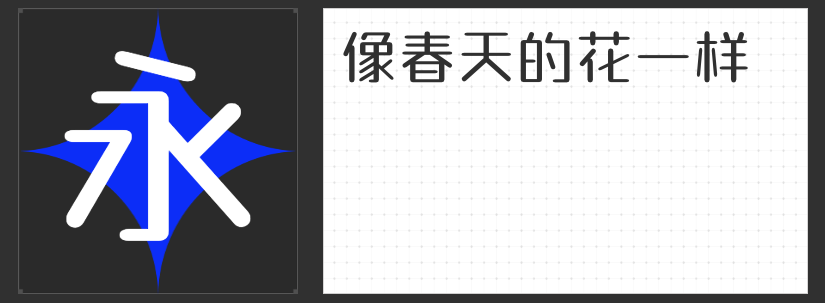
电商设计进阶指南:四款高辨识度字库字体解锁视觉吸引力
在电商视觉竞争白热化的当下,字体的选择直接影响用户的第一眼印象。从主图文案到活动海报,从商品详情页到品牌标语,一款兼具个性与实用性的字体能瞬间提升信息传达效率。以下四款专为电商场景设计的字库字体,以独特风格满足不同品类的视觉需求,助力品牌在海量信息中脱颖而出。
一、励字笑语窃窃简
这款字体以“圆融”为核心设计语言,笔画采用柔和的圆弧转角,彻底摒弃尖锐棱角,营造出如气泡般轻盈的视觉体验。其字形结构中巧妙融入留白空间,既避免臃肿感,又强化了“萌动”气质。笔画粗细过渡自然,在保持可爱风格的同时确保远距离可读性,尤其适合母婴、宠物、文创等需要传递温暖感的品类,通过字形传递“友好”“亲切”的品牌态度。
二、字恋狂嗨玩简
以儿童积木为灵感,这款字体通过夸张的粗壮笔画与方块字形构建出笨拙却灵动的视觉张力。重心下沉的设计赋予字体“扎根感”,仿佛每个字符都稳稳站立,与电商场景中“稳定”“可靠”的隐性诉求不谋而合。方中带圆的笔画处理弱化了机械感,在保持现代简约风格的同时注入童趣基因,是潮玩、零食、数码配件等年轻化品牌突破同质化的利器。
三、励字粗圆简繁
针对家电、家居、美妆等需要传递专业感的品类,这款字体以“方正饱满”的结构奠定稳重基调。笔形柔和却不失力度,粗细均匀的笔画在视觉上形成安全屏障,搭配较大的字面设计,确保在缩略图或移动端展示时依然清晰可辨。无论是主打性价比的促销文案,还是强调品质感的产品标语,都能通过字形传递“值得信赖”的品牌形象。
四、励字魔方黑简
在信息过载的电商页面中,这款字体以“视觉冲击力”为核心优势。方头方尾的笔形设计彻底去除装饰性元素,横竖笔画粗细对比形成强烈反差,如同魔方块般棱角分明。极简的结构使其在缩小后依然保持高辨识度,特别适合作为主标题字体应用于搜索关键词、限时折扣等核心信息区,通过字形本身的张力引导用户视线,提升点击转化率。
从萌系治愈到极简醒目,从年轻化表达至专业感传递,这四款字体覆盖了电商设计的多元需求。它们不仅是对文字的视觉重构,更是品牌与用户之间无声的对话——通过字形传递温度、态度与价值,让每个字符都成为提升转化率的隐形推手。